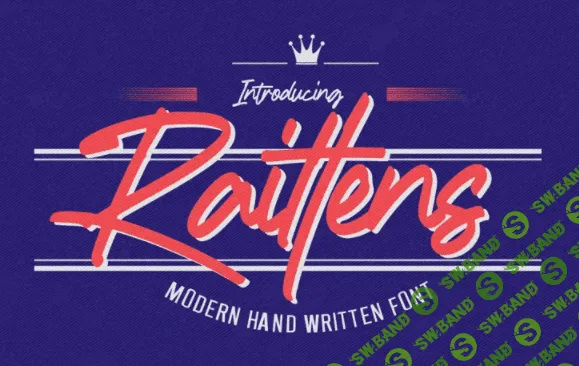
Название: Raittens Font (2021)
Современный рукописный шрифт Raittens - это фирменный стиль и стильный стиль, этот шрифт отлично подойдет для ваших творческих проектов, таких как водяной знак на фотографии, а также для логотипов и брендинга, приглашений, рекламы, дизайна продукции, канцелярских товаров, свадебных дизайнов, этикеток, упаковки продукции, специальных мероприятий или всего, что требует рукописного вкуса.
Raittens - это естественный рукописный шрифт. Этот шрифт ручной работы придаст вашему дизайну естественную красоту каждой детали. Он идеально подходит для любого дизайнерского проекта, как приглашение, логотип, обложка книги, ремесло или любые цели дизайна, фотографии наложения, знаки, окна искусства, скрапбукинг, теги и многое другое!
Название: Raittens Font (2021)
Современный рукописный шрифт Raittens - это фирменный стиль и стильный стиль, этот шрифт отлично подойдет для ваших творческих проектов, таких как водяной знак на фотографии, а также для логотипов и брендинга, приглашений, рекламы, дизайна продукции, канцелярских товаров, свадебных дизайнов, этикеток, упаковки продукции, специальных мероприятий или всего, что требует рукописного вкуса.
Raittens - это естественный рукописный шрифт. Этот шрифт ручной работы придаст вашему дизайну естественную красоту каждой детали. Он идеально подходит для любого дизайнерского проекта, как приглашение, логотип, обложка книги, ремесло или любые цели дизайна, фотографии наложения, знаки, окна искусства, скрапбукинг, теги и многое другое!